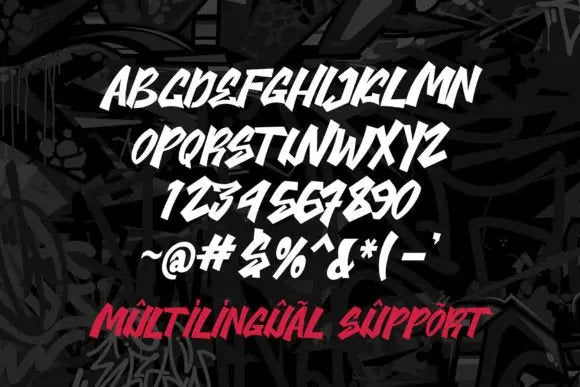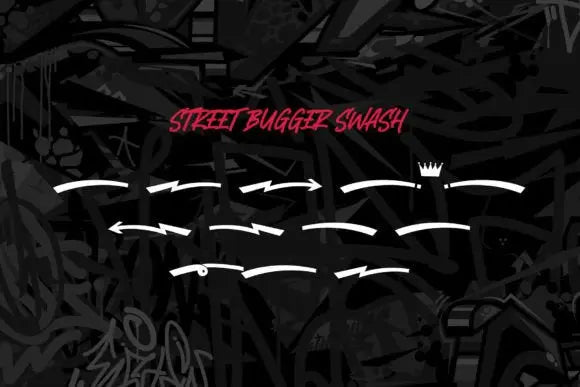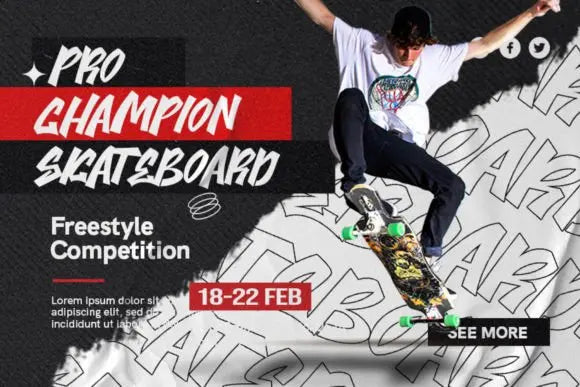
Fuente Street Bugger
El arte del graffiti cobra vida con la atrevida y dinámica fuente “Street Bugger”, aderezada con distintivos caracteres decorativos. Conocidas por su encanto audaz y expresivo, las fuentes de graffiti llaman la atención y “Street Bugger” hace precisamente eso, pero con un toque único.
Cada curva y línea de esta fuente tiene un estilo añadido, cortesía de los caracteres decorativos floridos, que amplifican su energía creativa.
Capturando a la perfección el coraje urbano y la vibra vanguardista del arte callejero, “Street Bugger” brilla en una infinidad de aplicaciones, desde carteles vibrantes hasta iniciativas inspiradas en el arte callejero o cualquier proyecto imaginativo que requiera un toque de tipografía audaz y expresiva.